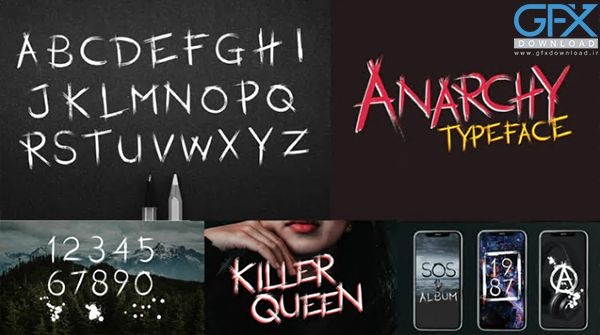
پروژه افتر افکت متن متحرک با نام Anarchy Animated Typeface. یک قالب ویدئویی شگفت انگیز است که شامل کل الفبای انگلیسی و اعداد 0-9 است. می توانید از این پروژه متن متحرک مخصوص افتر افکت برای ساخت انیمیشن های کلمه ای منحصر به فرد خود استفاده کنید. برای ایجاد نتایج جالب می توانید از کنترلر هوشمند رنگ استفاده کنید. می توانید از آنها در ارائه ها ، نمایش اسلایدها ، تبلیغات و فیلم های رویداد استفاده کنید. مخاطبان خود را با این پروژه آماده افتر افکت پویا و متحرک جذب کنید. بدون نیاز به پلاگین و کیفیت HD.